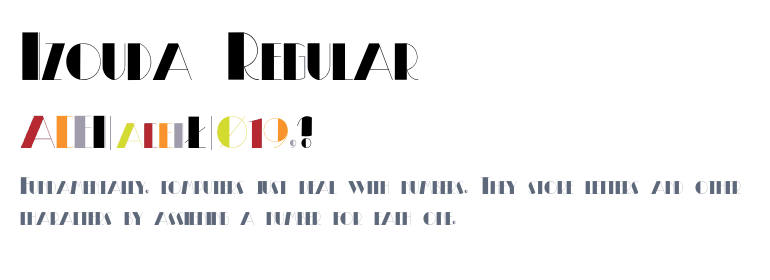
Welche Schriftart auf diesem Sticker
ich suche nach dem Namen der Schriftart auf diesem Sticker.
Ob es genau diese als elektroischen Font gibt, wage ich zu bezweifeln. Ähnliche findest du mit den Stichwörtern "Art Deco" oder "Burlesque", beispielsweise Izouda.